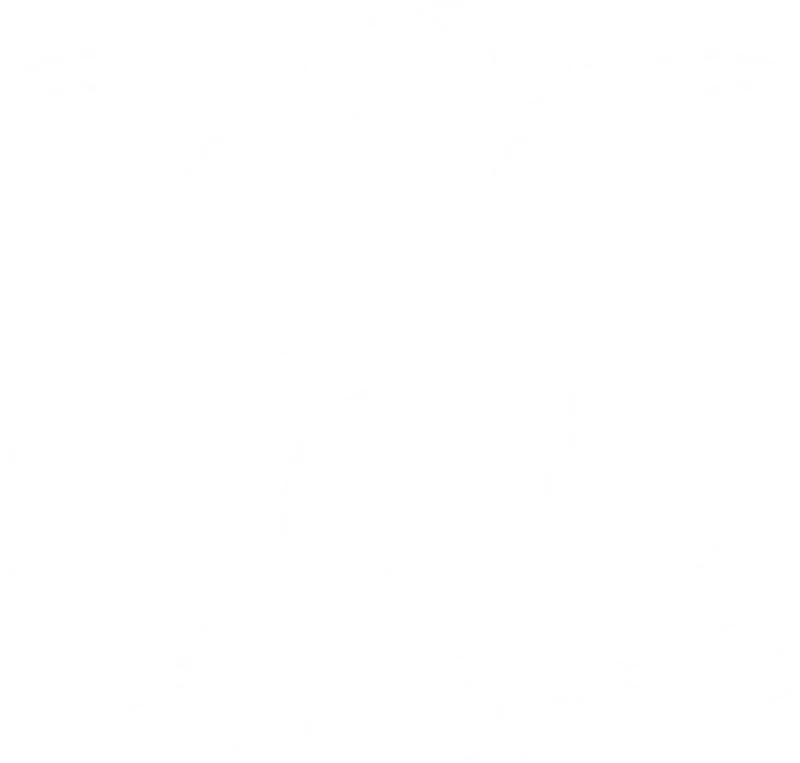
Thông điệp "Honor God" ý nghĩa, font chữ độc đáo
Thông điệp "Honor God" ý nghĩa, font chữ độc đáo — Thiết kế chữ "Honor God" độc đáo, mang thông điệp ý nghĩa về tôn vinh Chúa. Phù hợp in áo, túi, sticker. Có thể áp dụng công nghệ in DTF.
Trong hình có: chữ viết, thiết kế đồ họa
Phong cách: vintage · Cảm giác: mạnh mẽ